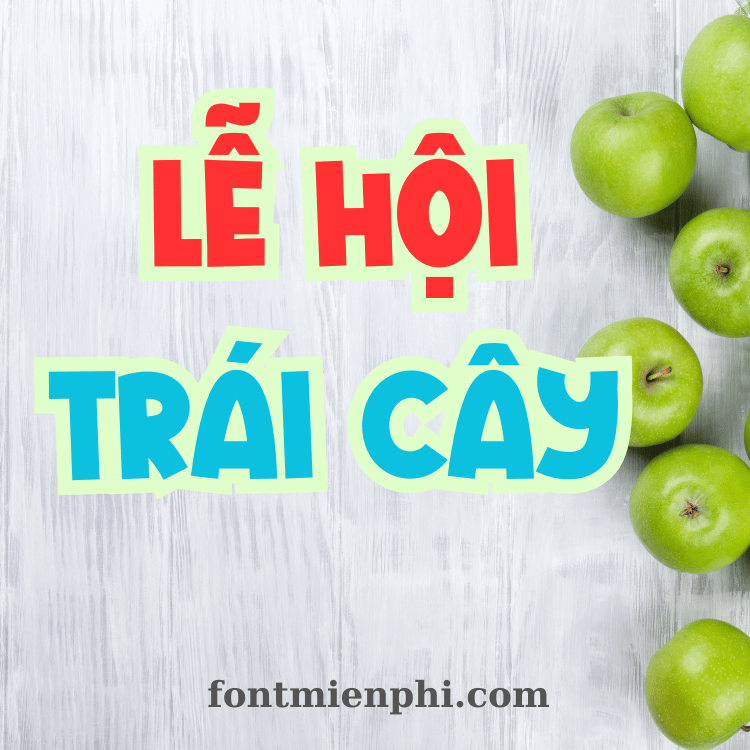
Font Kidsco Việt hóa VIP
Tải Font Kidsco Việt hóa VIP – Bộ Font Chữ Hoàn Hảo Cho Giáo Dục Trẻ Em
Giới thiệu về bộ Font Kidsco Việt hóa VIP
Trong lĩnh vực thiết kế giáo dục, việc lựa chọn một bộ Font Chữ phù hợp đóng vai trò quyết định đến khả năng tiếp nhận thông tin của trẻ nhỏ. Bộ Font Kidsco Việt hóa VIP là phiên bản cao cấp được thiết kế riêng biệt nhằm mang lại sự vui nhộn, thân thiện và cực kỳ dễ đọc. Với các đường nét bo tròn mềm mại và phong cách tinh nghịch, bộ font này giúp các sản phẩm thiết kế dành cho học sinh trở nên sinh động và lôi cuốn hơn bao giờ hết.
Tại sao nên sử dụng Font Kidsco cho học sinh?
Đặc điểm nổi bật của Font Miễn Phí này chính là tính ứng dụng cao trong môi trường học đường. Font Kidsco Việt hóa VIP không chỉ hỗ trợ đầy đủ bảng mã tiếng Việt có dấu mà còn được tinh chỉnh khoảng cách ký tự hoàn hảo. Điều này giúp các thầy cô giáo và phụ huynh dễ dàng tạo ra các bài giảng, bảng chữ cái hoặc nhãn vở đẹp mắt mà không lo lỗi hiển thị. Sự chỉn chu trong từng nét chữ giúp khơi gợi cảm hứng học tập và sự sáng tạo cho các em nhỏ ngay từ cái nhìn đầu tiên.
Ứng dụng đa dạng của Font Kidsco Việt hóa VIP
Bộ font này cực kỳ đa năng, phù hợp cho nhiều mục đích khác nhau từ in ấn đến trình chiếu kỹ thuật số. Bạn có thể sử dụng Font Kidsco Việt hóa VIP để thiết kế bìa sách thiếu nhi, làm poster cho các sự kiện trường học hoặc tạo menu cho các quán ăn dành cho trẻ em. Với định dạng tệp linh hoạt, font chữ này tương thích tốt trên các phần mềm đồ họa phổ biến và các ứng dụng văn phòng cơ bản.